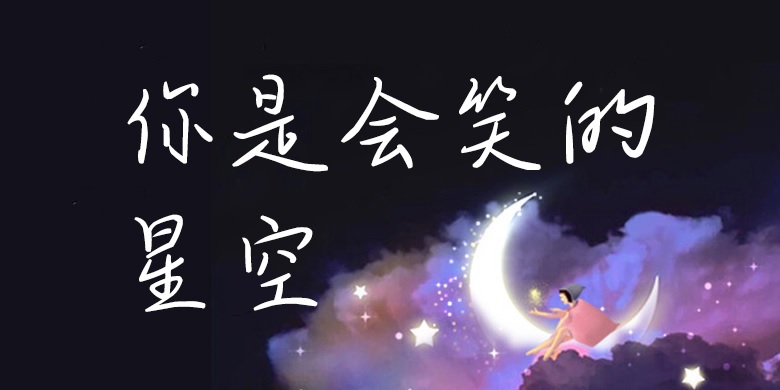
品牌:方正手迹设计师:俞亦婷发行时间:2020字库编码:简繁扩展(GBK)分类:常规书写·硬笔字体属性:精品字
该字用楷书的笔意去表达行书,但在构字上又多变化,从容不迫而又姿态万千。良好的留白,使得该字具有较好的透气性,因而在阅读舒适性上会有比较清新的体验。适用于文艺类的书刊、品牌广告和产品包装设计,以及社交网络的个性化用字。